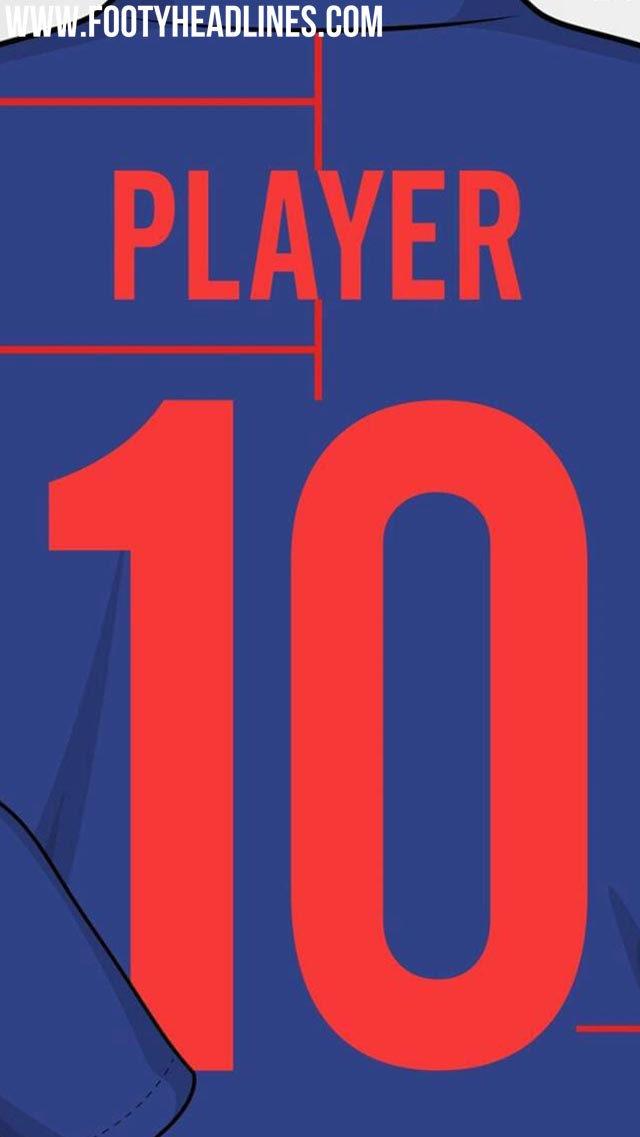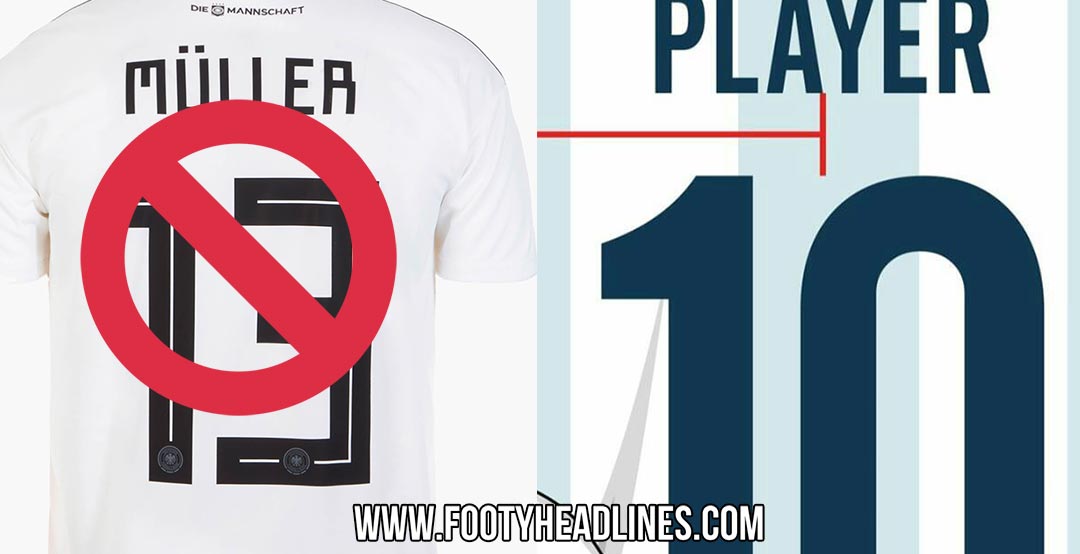
Völlig neue Adidas 2019 Trikot-Schriftart geleakt
Adidas wird 2019 eine neue Schriftart für Fußballtrikots auf den Markt bringen. Die neue Adidas 2019 Trikot-Schriftart, die für viele Trikots der Adidas-Teams wie z.B. die Copa America 2019 Trikots der Marke verwendet wird, ersetzt die berüchtigte Adidas WM 2018 Schriftart.
Die offizielle Schriftart von Adidas, die für die Trikots der FIFA Weltmeisterschaft verwendet wurde, sorgte für Verwirrung, da sie quadratische, kyrillische Buchstaben und Zahlen enthielt. Die Schriftart der Weltmeisterschaft 2018 wurde von der traditionellen sowjetischen Bildsprache inspiriert. Die Schriftart verwendet scharfe 90-Grad-Schläge, was zu Verwechslungen zwischen Buchstaben wie 'A' und 'R' &'X' und 'K' führt.
Adidas 2019 Trikot-Schriftart - Wird bei Copa America 2019 verwendet
Die neue Adidas 2019 Trikot-Schriftart, die einen weitaus weniger irritierenden Stil als die Schriftart der WM 2018 hat, setzt auf einen modernen Stil mit häufig modischen Buchstaben und Zahlen.
Der Adidas 2019 Schriftart soll in Kürze erscheinen. Nationalmannschaften wie Deutschland, die kein neues Trikot für 2019 veröffentlichen werden, werden die 2018-Schriftart logischerweise weiterhin verwenden.